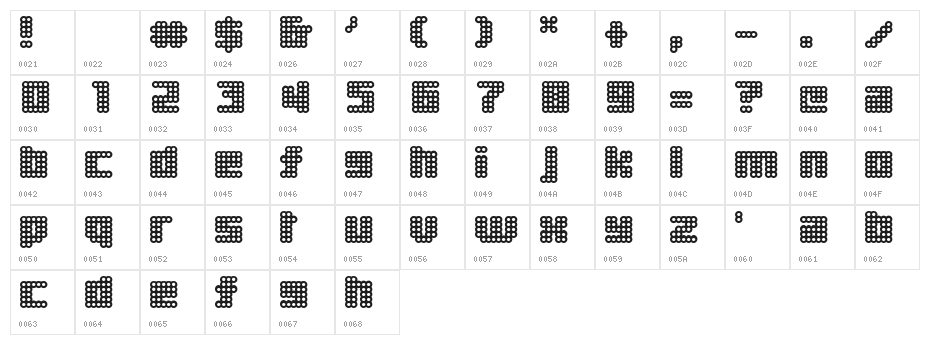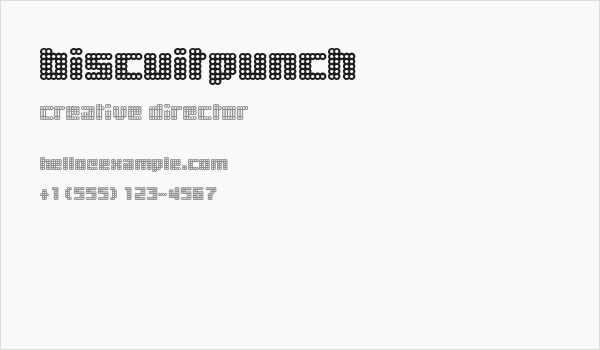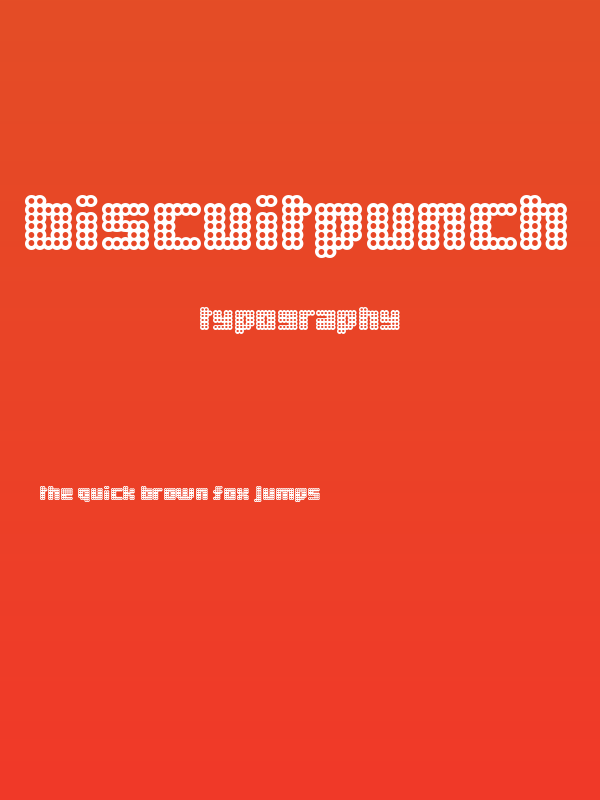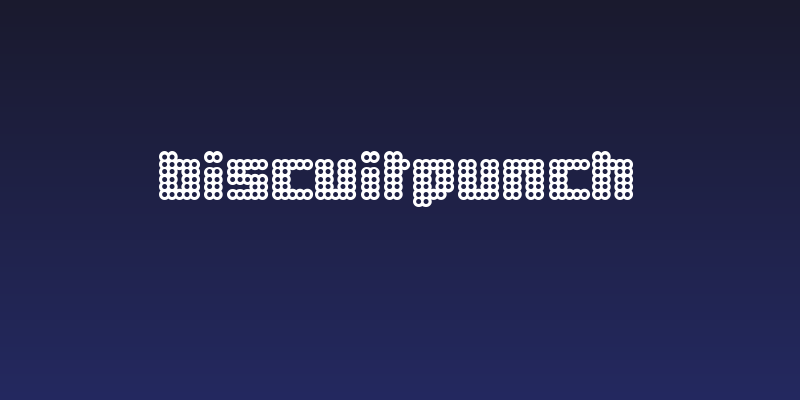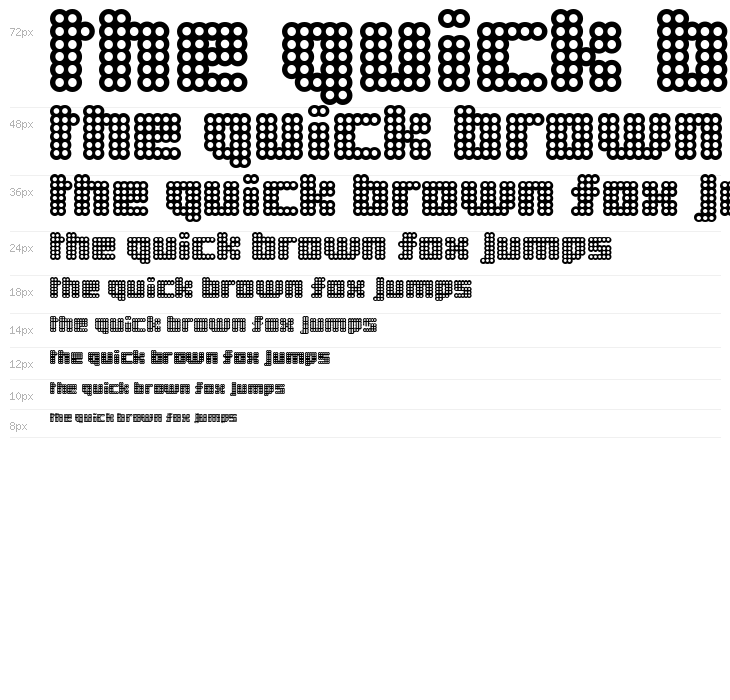
BiscuitPunch Font
✎ Dotted
| Anwendungsfall | Logos, Posters, Digital Art |
| Vorgeschlagene Projekte | Ideal for creative projects such as posters, logos, and digital art where a unique and eye-catching font is needed. |